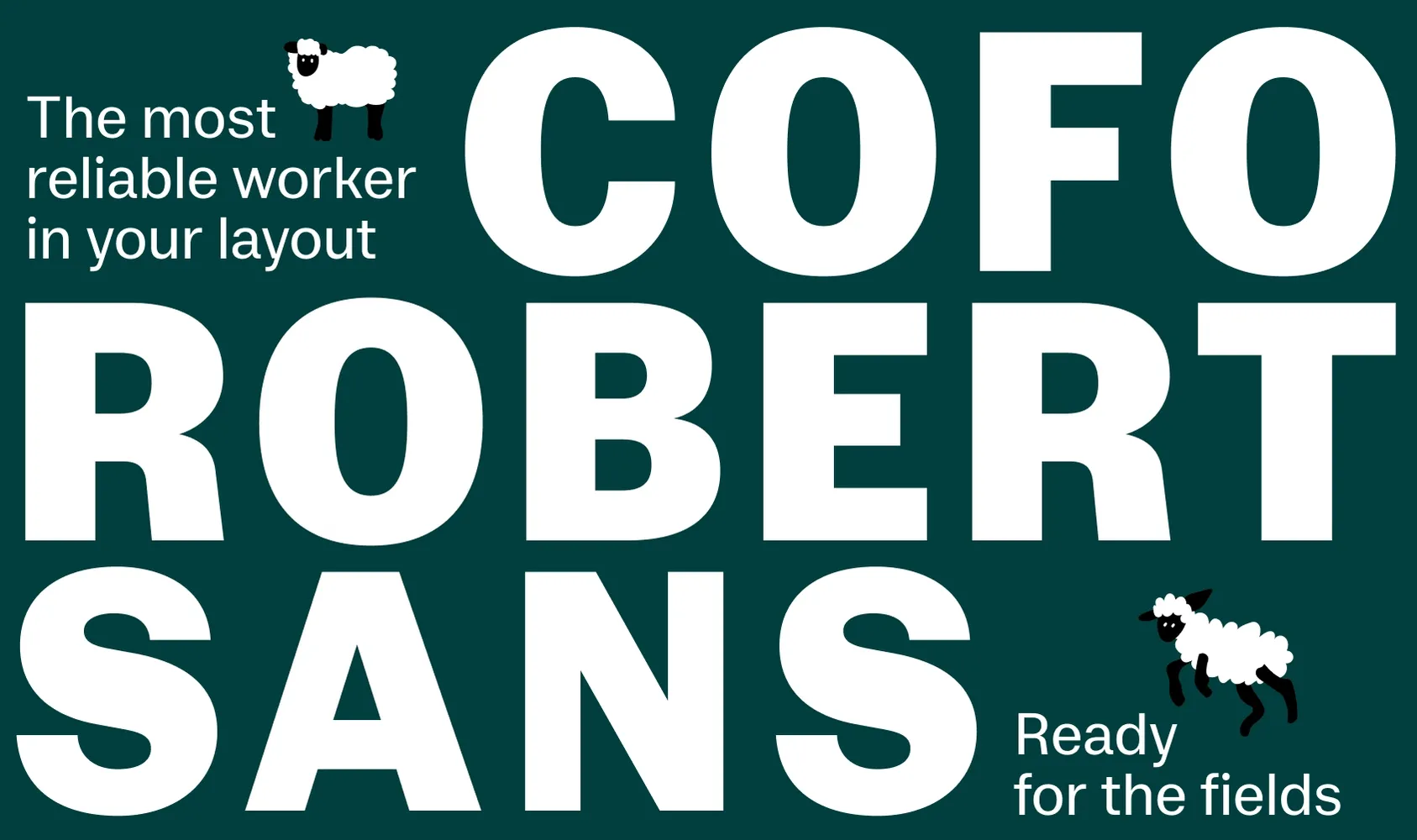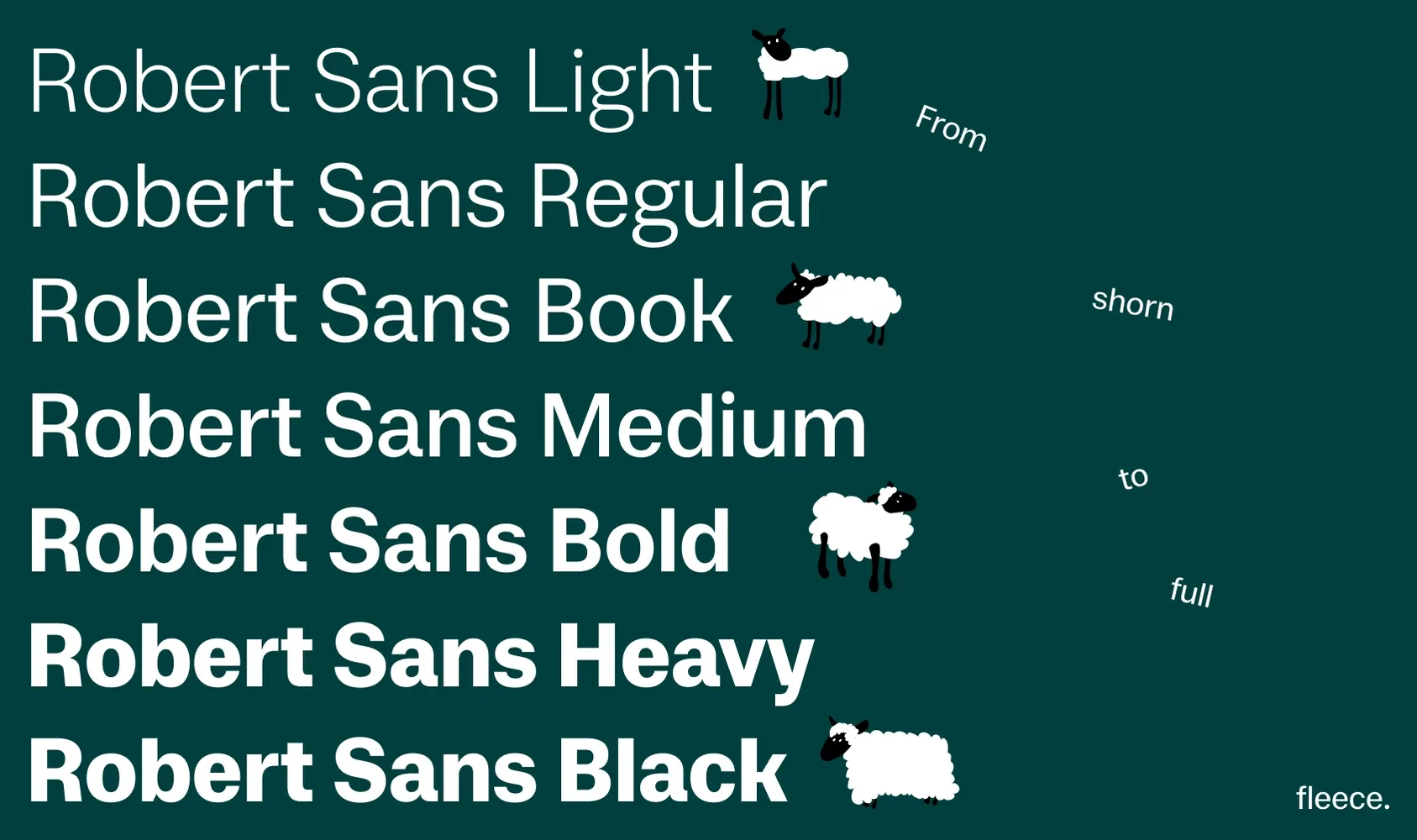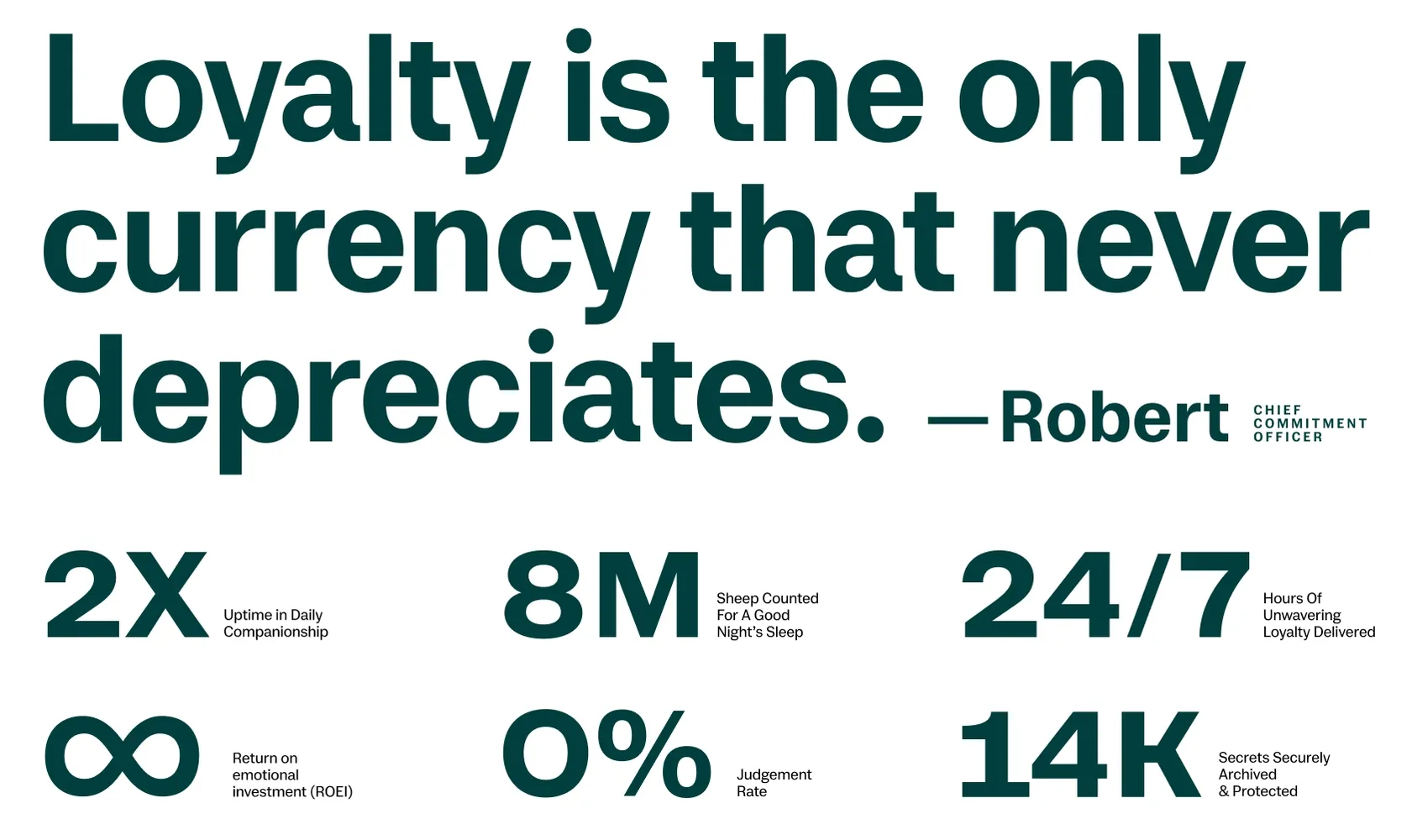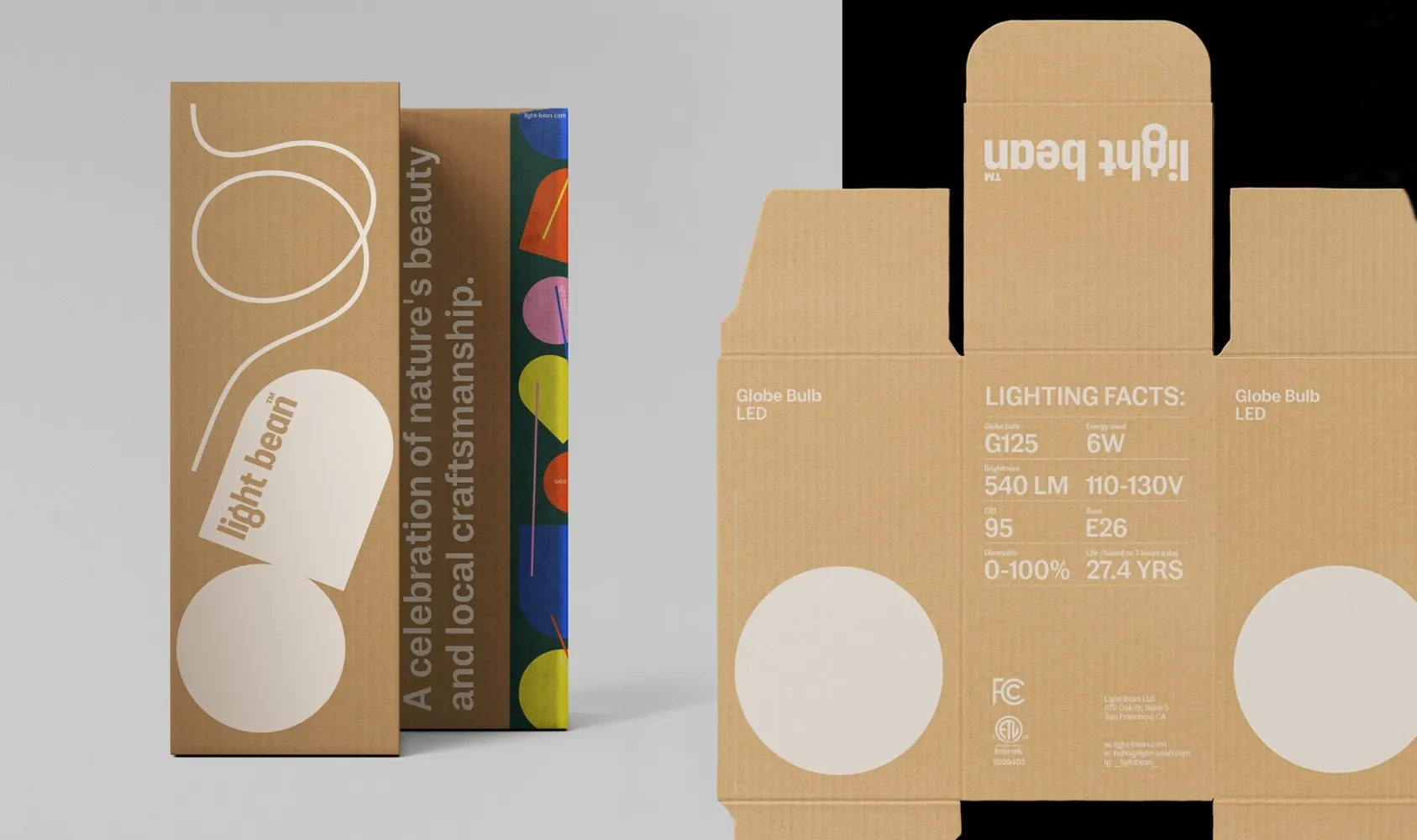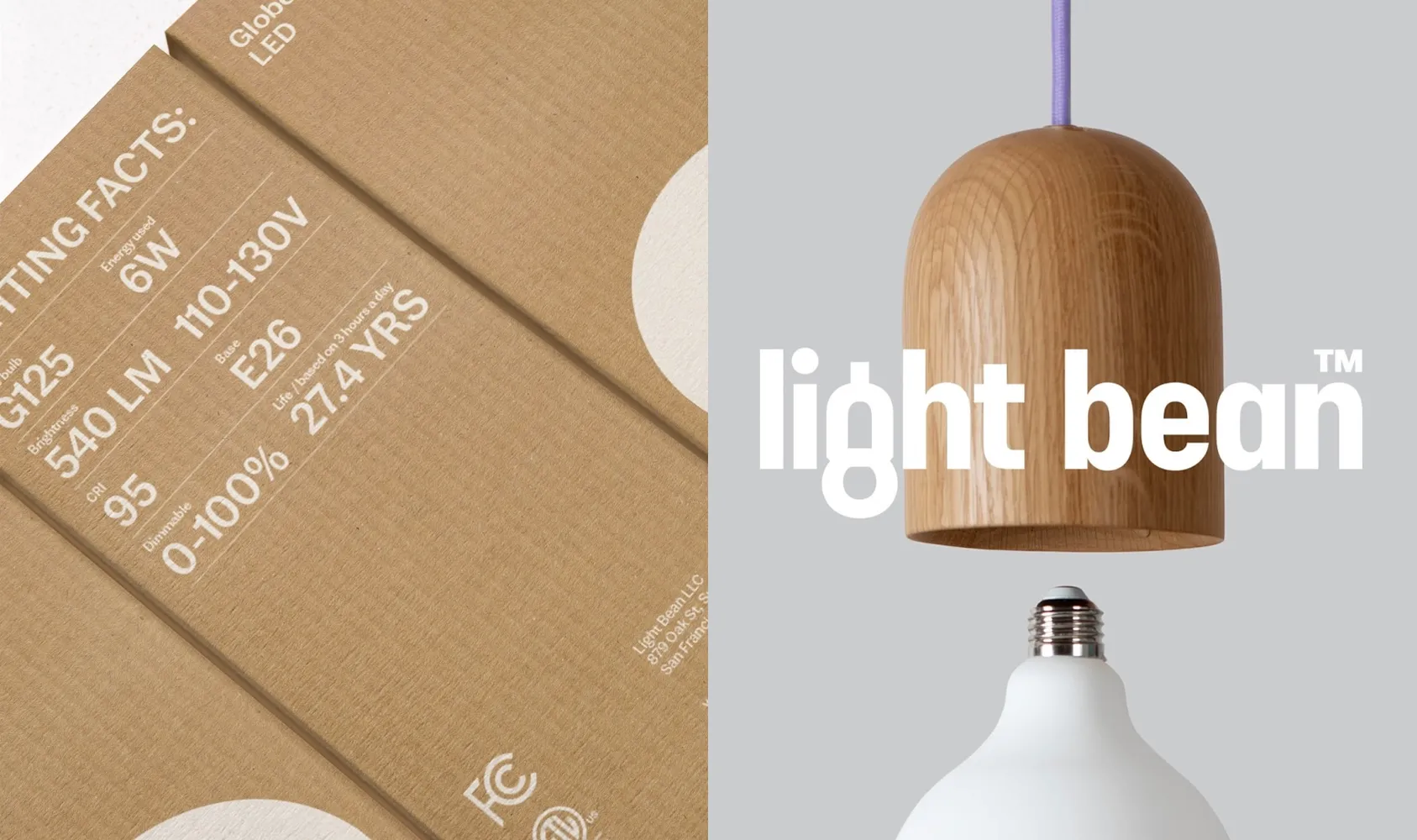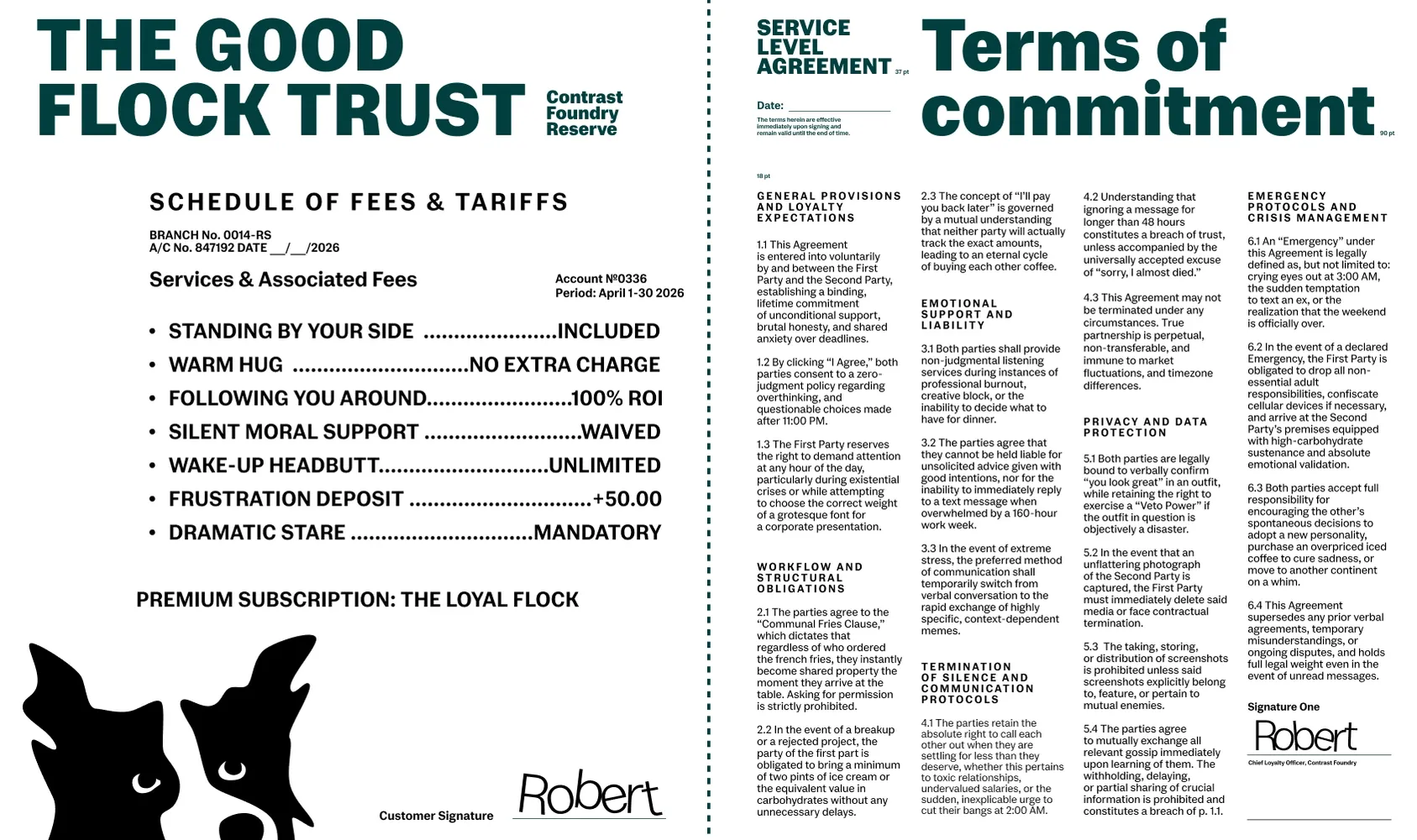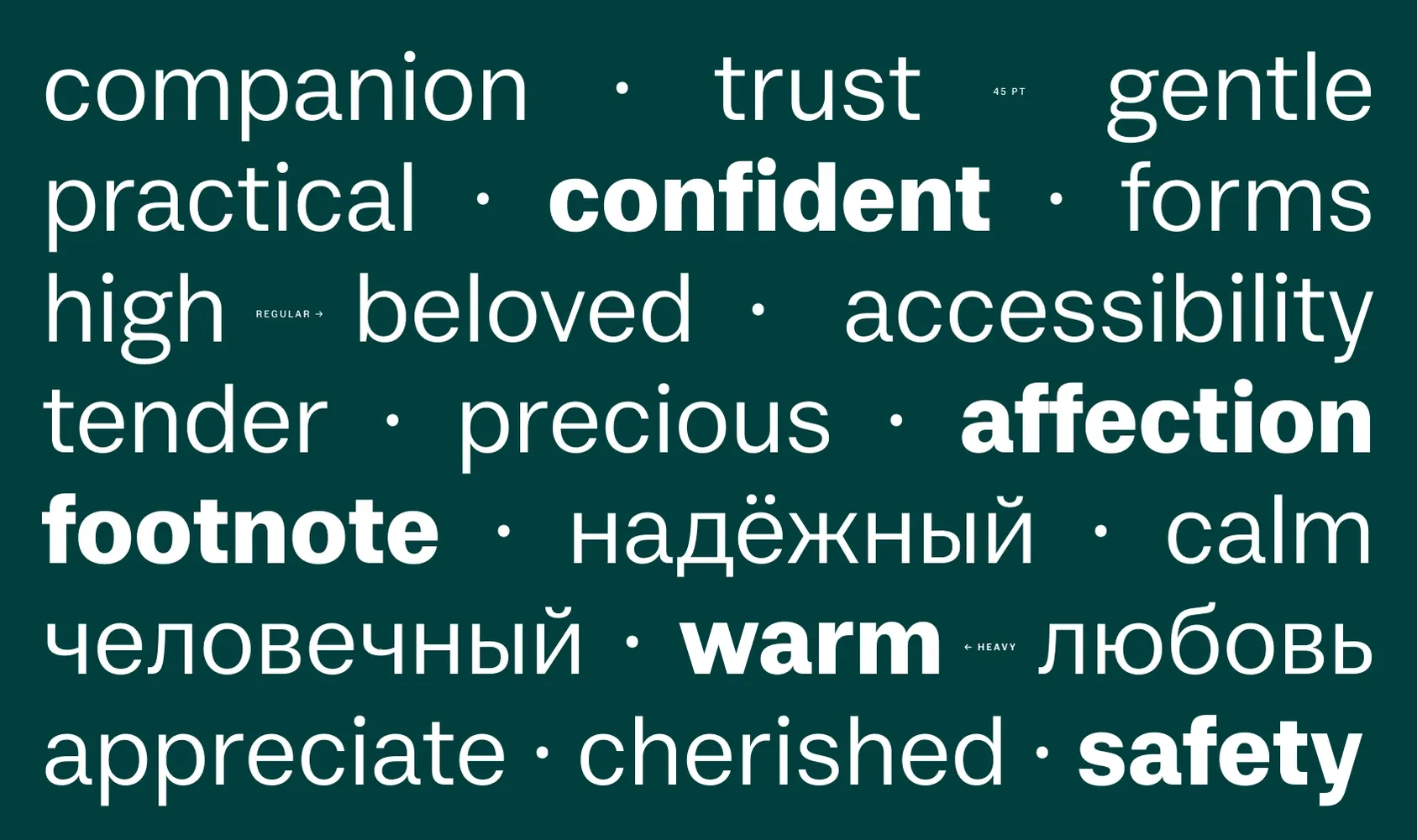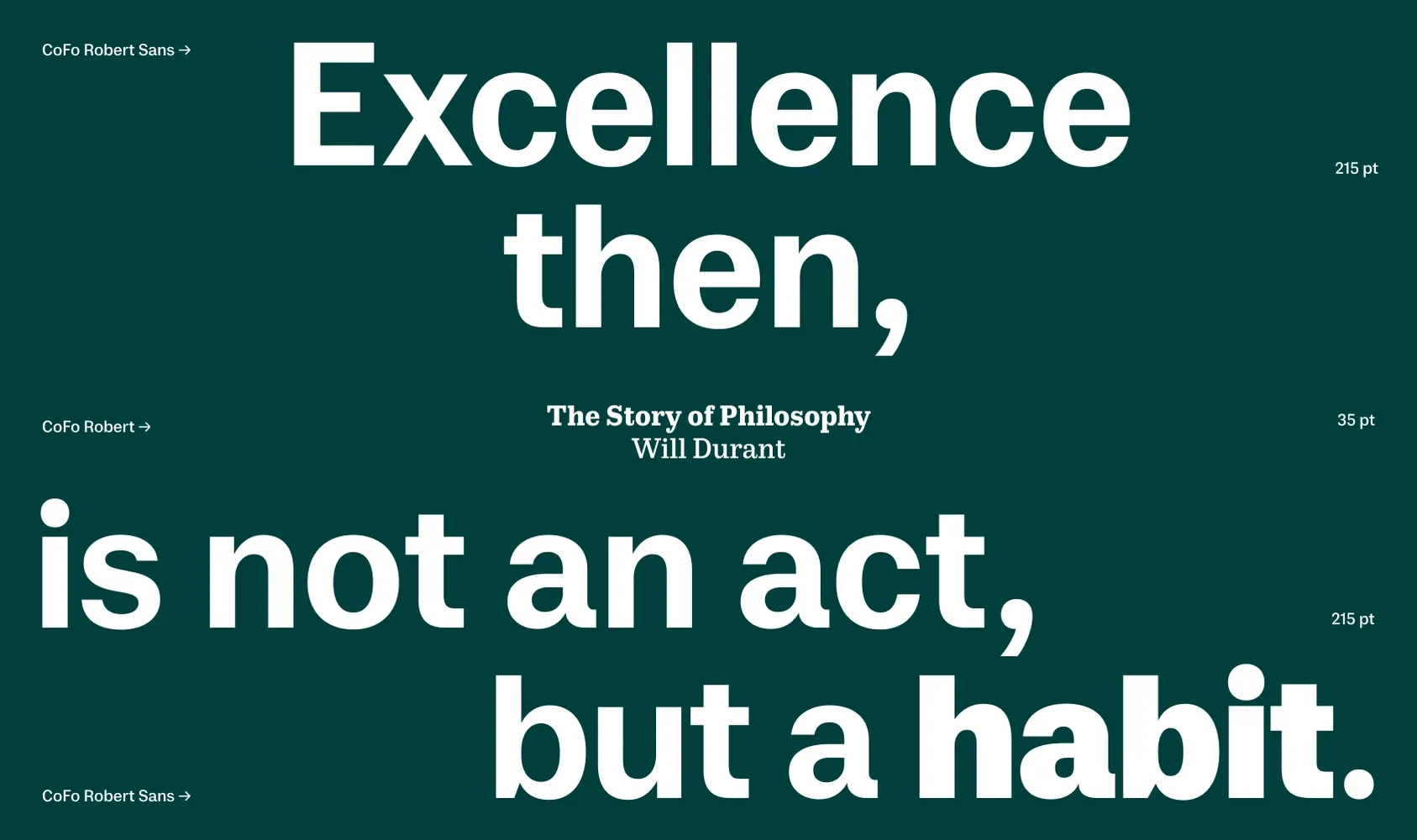
Robert Sans
Light, Regular, Book, Medium, Bold, Heavy, Black
CoFo Robert Sans—это функциональный, ёмкий гротеск, в котором неожиданно нашлось место живости и теплу. Он унаследовал свои формы от брускового CoFo Robert и получился рабочим, удобным, и при этом с характером.
Часто формы гротесков упрощаются до такой степени, что становятся механическими CoFo Robert Sans предлагает посмотреть на универсальный гротеск по-новому—таким, каким он мог бы быть, если добавить в него чуть больше тепла. Его особенности почти незаметны при первом взгляде, но очень ощущаются в работе: умеренный контраст штрихов, выверенные пропорции, мягкие изгибы. Всё вместе это придаёт шрифту энергию и яркость, не мешая при этом оставаться надёжным инструментом для любых задач.
В знаковом составе есть всё, что нужно для серьёзной работы: капитель, верхние и нижние индексы, включая цифры и буквы латиницы и кириллицы, минускульные, маюскульные и капительные цифры.
CoFo Robert Sans—это тот самый рабочий гротеск, который легко подружится с любым проектом.
Дизайнер: Лиза Рассказова
Начертания: Light, Regular, Book, Medium, Bold, Heavy, Black